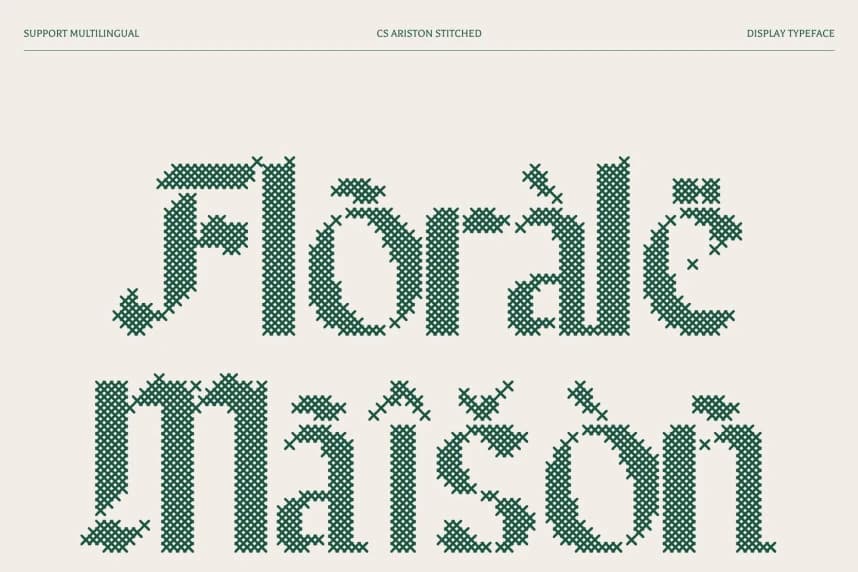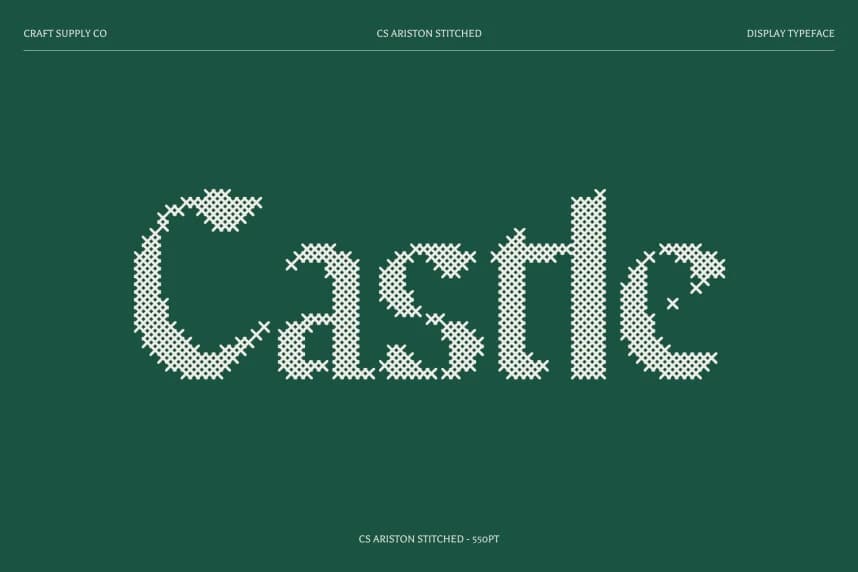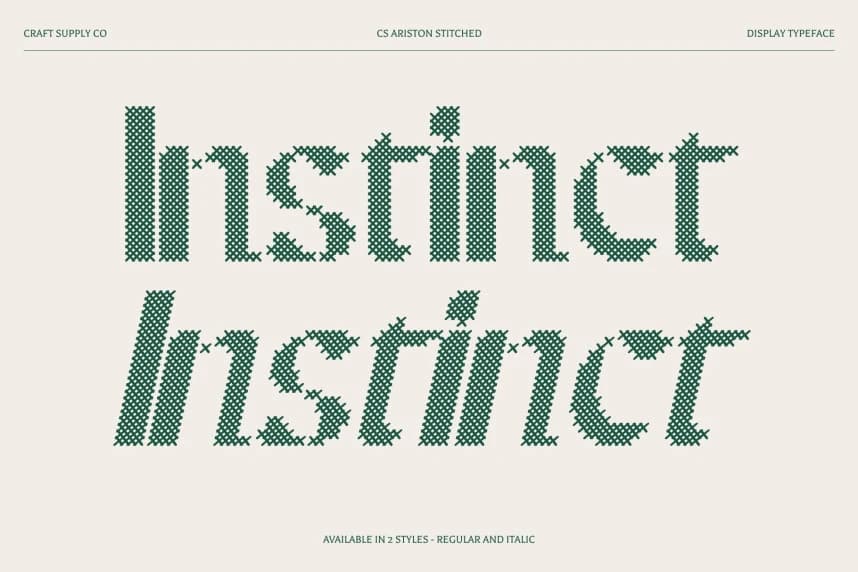
CS Ariston Stitched Font
CS Ariston Stitched Font – Blackletter Font: Gelenek, Cesur Zarafetle Buluşuyor. Klasik Blackletter El işçiliğiyle derinlik kazanıyor. Bu, Blackletter geleneğinin zamansız zarafetini yansıtan bir gösterim serif yazı tipidir.
CS Ariston Stitched Font – Blackletter Font: Gelenek Cesur Zarafetle Buluşuyor. El Yapımı Derinliğe Sahip Klasik Blackletter. Bu, Blackletter geleneğinin zamansız zarafetini yansıtan bir gösterim serif yazı tipidir.